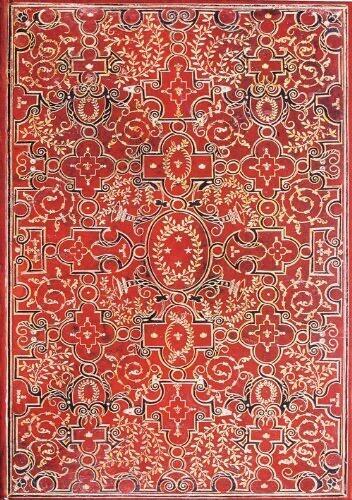
Biblia Sacra. Das Buch der Bücher.
Der Verlag sagt: 180 Exemplare des bedeutendsten Buchs des Abenlandes – Illuminierte Handschriften des Mittelalters, eine der ersten Blockbuch-Ausgaben der Biblia Pauperum, Inkunabeln, darunter zwei komplette Pergamentexemplare der 48zeiligen Bibel von Fust & Schöffer, Bibeln des 16. und 17. Jahrhunderts mit Holzschnitten und Kupferstichen, Prachtausgaben des 18. und 19. Jahrhunderts, monumentale Ausgaben des 20. Jahrhunderts.
Rezension
Das Buch des Buches der Bücher
Der Antiquar Heribert Tenschert präsentiert in einem üppigen Katalog hinreißende Bibeldrucke aus sechs Jahrhunderten
von Martin Z. Schröder
Vom Antiquar Heribert Tenschert in Ramsen am Rhein ist erneut eine Sensation zu berichten. Nein, es ist noch nicht ganz so weit, daß er die weltweit größte Sammlung von Stundenbüchern besitzt, diese illustrierten Gebetsbücher für die private Andacht von Laien, welche Auszüge aus dem kirchlichen Meßbuch für verschiedene Tageszeiten enthalten. Die große Sammlung Tenscherts, größer als die der British Library, aber noch nicht so groß wie die der Bibliothèque nationale de France, wurde vor einiger Zeit in der Berliner Staatsbibliothek gezeigt, danach in Paris, München, Zürich, Genf und Cambridge. Nein, diesmal keine Stundenbücher.
Der Katalog, der jetzt aus Tenscherts Domizil, der Bibermühle, kommt, kündet von der Sensation des Privatbesitzes von zwei Fust-Schöffer-Bibeln. Johann Fust war der Geldgeber Gutenbergs, der, nachdem er Gutenberg erfolgreich verklagt hatte, mit dem Kalligraphen und Mitarbeiter Gutenbergs, Peter Schöffer, die Offizin Fust & Schöffer gründete. Das letzte Mal, daß zwei Exemplare der B 48, wie man die 48zeiligen Fust-Schöffer-Bibeln nennt, auf Pergament zusammen angeboten wurden, war 1769 im Katalog von Louis Jean Gaignat. Der hatte allerdings nur ein illuminiertes. Zwei illuminierte auf Pergament hat es noch nie in Privatbesitz gegeben! Im Jahr 1462 wurden sie als Luxusprodukte gedruckt, und jeder Käufer der Druckbogen ließ sie sich vom Illuminator seiner Wahl ausmalen und von einem Buchbinder je nach Wertschätzung des Werkes und Geldvermögen binden. Eines der beiden doppelbändigen Exemplare wurde vom als „Fust-Meister“ bekannten Künstler illuminiert und sehr viel später in violette quergenarbte Maroquinbände der ersten Hälfte des 19. Jahrhunderts gebunden, welche mit dem Wappen des Earl of Carysfort versehen sind. Es ist mit 4 Millionen Euro das teurere der beiden. Das zweite Exemplar dieses Buchpaares wurde wahrscheinlich von drei verschiedenen Malern in einem norditalienischen Atelier illuminiert. Auch dieses Buch wurde mehrmals neu gebunden, zuletzt im 18. Jahrhundert unter Beibehaltung der alten Holzdeckel und Messingbeschläge.
Großartig an diesem Katalog sind die hervorragenden Fotos. Hier wurde nicht einfach gescannt, sondern speziell die Hüllen der Bücher aus Pergament und Leder, immer geschmückt, oft reich vergoldet, wurden so sorgfältig ausgeleuchtet, daß auch die herrlichen Blindprägungen in tiefschwarzem Leder deutlich zu sehen sind und man einen Eindruck bekommt von der überwältigenden Buchhandwerkskunst vergangener Jahrhunderte.
180 Exemplare des bedeutendsten Buches des Abendlandes bietet Tenschert zum Kauf an und zeigt und erläutert er in seinem wunderbaren Katalog: Bibeln des 16. und 17. Jahrhunderts mit Holzschnitten und Kupferstichen, Prachtausgaben des 18. und 19. Jahrhunderts und monumentale Ausgaben des 20. Jahrhunderts wie die drei Pergament-Exemplare des Psalters der Bremer Presse von 1929.
Heribert Tenschert erläutert jeden Artikel. Er beschreibt ausführlich die Ware, nur rein äußerlich, wie sich versteht, oft erklärt er die Herkunft der Bücher, und man kann daran sehr viel Freude haben, weil man die Begeisterung des kenntnisreichen Autors spürt, zum Beispiel wenn er am Ende der Beschreibung eines geschmiedeten orientalisierenden Lyonneser Flechtwerk-Silbereinbandes des 16. Jahrhunderts genau die Flecken und kleinen Löcher vom Rost der Nägel der Schließen aufzählt und schließlich kommentiert: „Insgesamt ein sehr schönes Exemplar in einem unerhörten Einband.“
Das wohl wichtigste Buch in diesem Katalog ist eine in Süddeutschland von in den Niederlanden geschnittenen Holzstöcken gedruckte Biblia Pauperum. Von diesem um 1464 gedruckten Blockbuch sind nur drei Exemplare bekannt, eines in Privathand. Tenscherts Anmerkung: „Es ist mit Sicherheit das schönste Exemplar einer Biblia Pauperum auf dem Markt seit fast 100 Jahren.“ Den Seltenheitswert dieses Buches erkennt der Laie nicht so rasch, denn es ist nur mit einer bräunlichen Tinte auf Wasserbasis abgerieben worden und nicht bunt ausgemalt.
Einige Bücher sind aber für jedermann sofort als ganz köstliche zu erkennen, vor allem die herrlichen, meist reich vergoldeten, gelegentlich mit farbigen Intarsien versehenen Lederbände, beispielsweise die von Christophe Plantin in Antwerpen gedruckte Bibel von 1583 in dem wohl größten bekannten Einband à la fanfare eine kunstvolle französische Bindung des späten sechzehnten Jahrhunderts. Auf einer Höhe von 44 Zentimeter und einer Breite von 30 sind in rotes, reichlich mit filigranen Ranken vergoldetes Maroquin feine schwarze Lederornamente als Intarsien eingefügt worden, dazu kommt eine ganz zarte graue Wachsfarbenmalerei. Es ist wirklich himmlisch, zumal wenn man sich vorstellt, wie weich sich dieses Leder in die Hand schmiegt.
Man wird fast traurig angesichts der meist lieblos gemachten Papierbündel, die heute in unseren Buchläden stehen. Heribert Tenschert hat den Haupttitel seines Buches außergewöhnlich auszustatten versucht, man könnte aber auch in seinem Buch die zahlreichen handwerklichen Fehler kritisieren. Unter typographischen Gesichtspunkten ist es eine Beleidigung: rote halbfette kursive Renaissance-Antiqua. Vor allem sieht man die Schwächen im Kontrast zu den abgebildeten Polyglotten- Bibeln, in denen bis zu acht Sprachen bebildert auf einer Seite zu stehen kommen und jede der Schriften mehr oder weniger eine Meisterleistung ist und auch der Satzspiegel den Kunstregeln entspricht.
Eine der schönsten Polyglotten ist die 1571 von Plantin gedruckte, deren interessante, den Geschäftsbüchern und Korrespondenzen des Druckers entnommene Geschichte Tenschert erklärt. Diese Bibel mit dem hebräischen Originaltext, einem syrischen, einer lateinischen Übersetzung des syrischen Textes, der lateinischen Vulgata und mit griechischem Text wurde unter der Schirmherrschaft des spanischen Königs Philipp II. produziert. Dieser hatte erst sechs Pergament-Exemplare bestellt, erhöhte dann aber auf dreizehn, wofür der Drucker 16.263 Kalbshäute beschaffen mußte. Heute sind noch vier oder fünf Pergamentexemplare bekannt; sie gehören dem Escorial in der Provinz Madrid, der British Library in London, der Biblioteca Nazionale in Turin, dem Vatikan in Rom, ein fünftes wird aus Salamanca gemeldet, die anderen gelten als verschollen. Und das von Tenschert ist für 225.000 Euro zu haben, wenn es nicht schon verkauft ist.